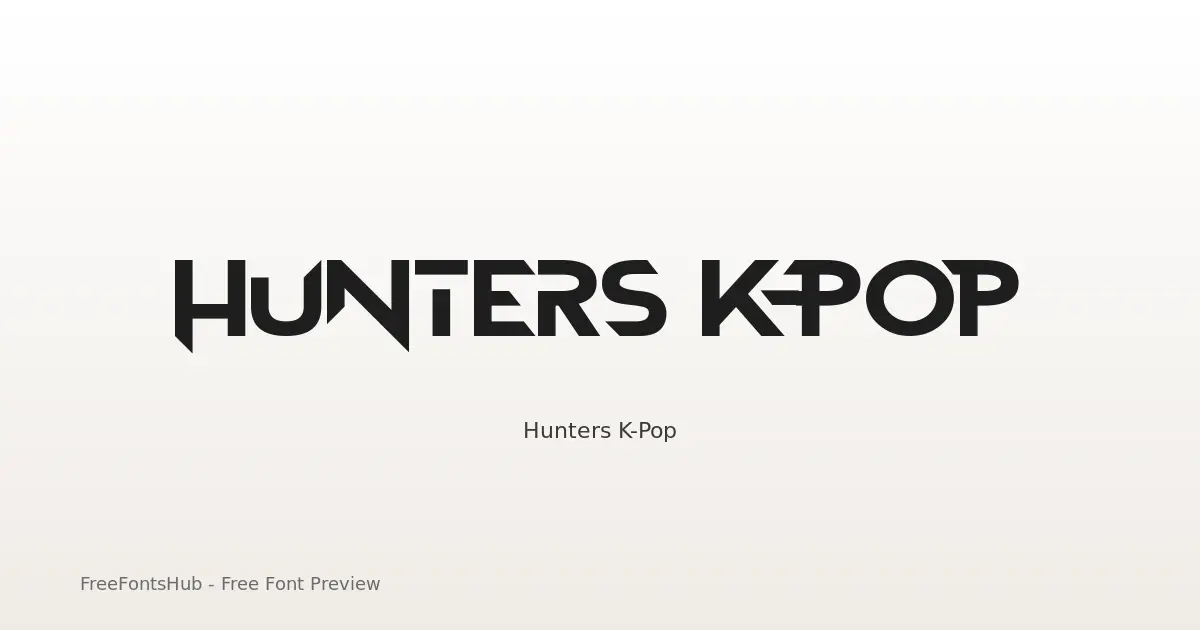
خط K-Pop Demon Hunters: أعد ابتكار سحر نتفليكس! 🎤⚔️
أعد ابتكار الجمالية الساحرة لفيلم نتفليكس K-Pop: Demon Hunters باستخدام خط "Hunters K-Pop" المجاني! مستوحى من الشعار الرسمي للفيلم، يجلب هذا الخط الجريء والمشرق بالنجوم طاقة الآيدول المطلقة إلى مشروع تصميمك القادم.
خط K-Pop Demon Hunters: أعد ابتكار سحر نتفليكس! 🎤⚔️
هل وقعت في حب الجمالية النابضة بالحياة لفيلم الفانتازيا الحضرية الموسيقي والرسوم المتحركة من نتفليكس، K-Pop: Demon Hunters؟ على الرغم من أن شعار الفيلم الرسمي المذهل تم رسمه خصيصاً بواسطة الفريق الموهوب في Picturemill، لا يزال بإمكانك جلب هذه الطاقة الساحرة ذاتها إلى مشاريع التصميم الخاصة بك!
نقدم لكم خط Hunters K-Pop من تصميم Chequered Ink. هذا الخط المجاني الرائع مستوحى بشكل كبير من طباعة الملصق الرسمي للفيلم، حيث يجسد بشكل مثالي الأجواء الجريئة والمليئة بالنجوم لفرقة الآيدول صائدي الشياطين. بفضل حروفه الحادة والديناميكية، يُعد الخيار الأمثل لرسومات المعجبين، وتصاميم أزياء الشارع، وملصقات الفعاليات الجذابة.